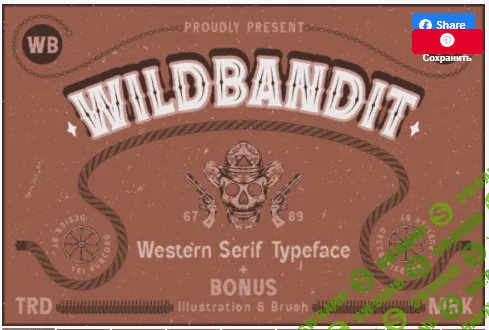
Название: Wild Bandit Font (2021)
Wild Bandit - это крутой, жирный шрифт в винтажном стиле. Он невероятно хорошо работает с плакатами, этикетками, брендингом и почти всем, что требует модного, напористого подхода. Этот шрифт закодирован в кодировке PUA, что означает, что вы можете легко получить доступ ко всем глифам и штрихам!